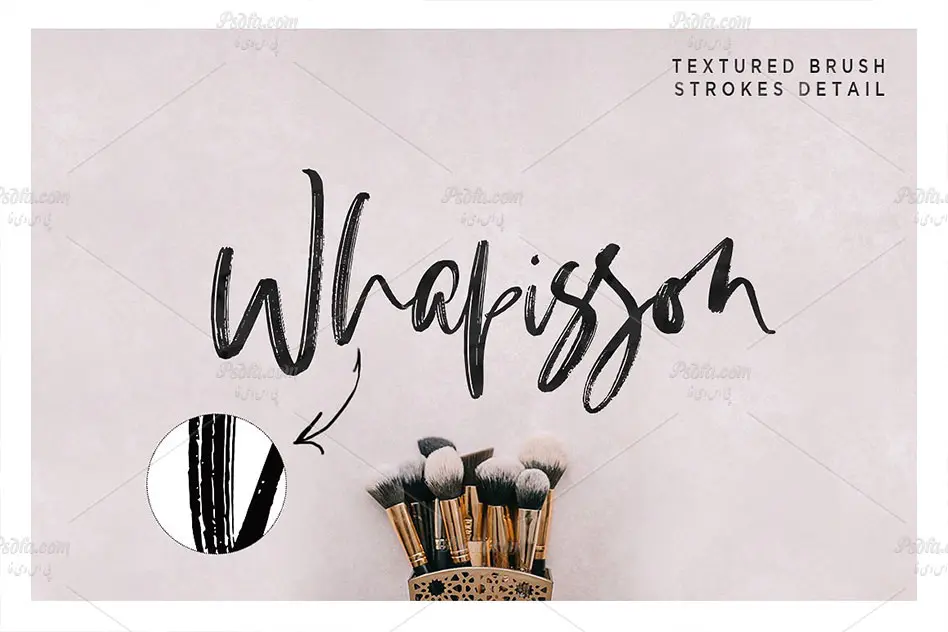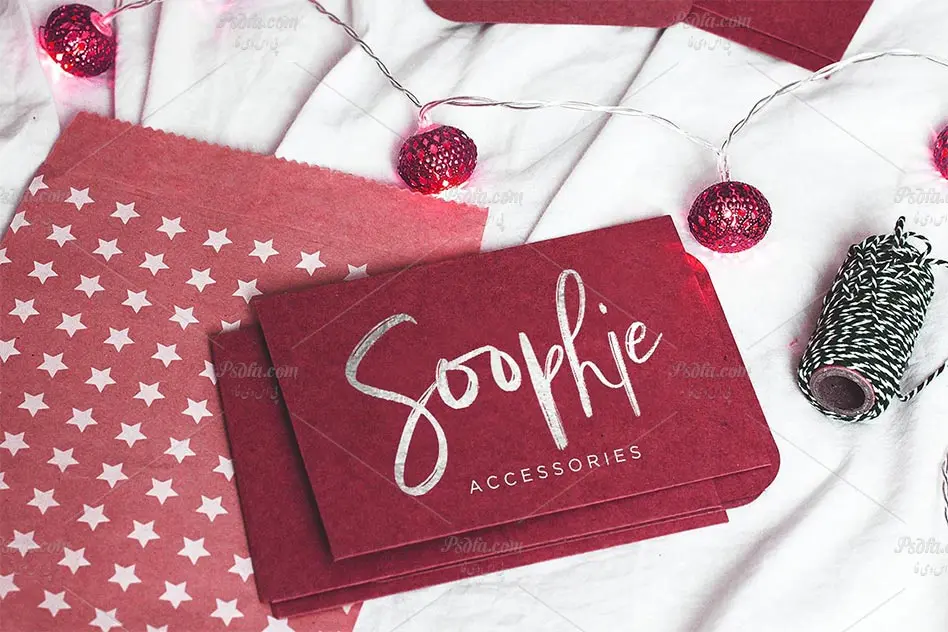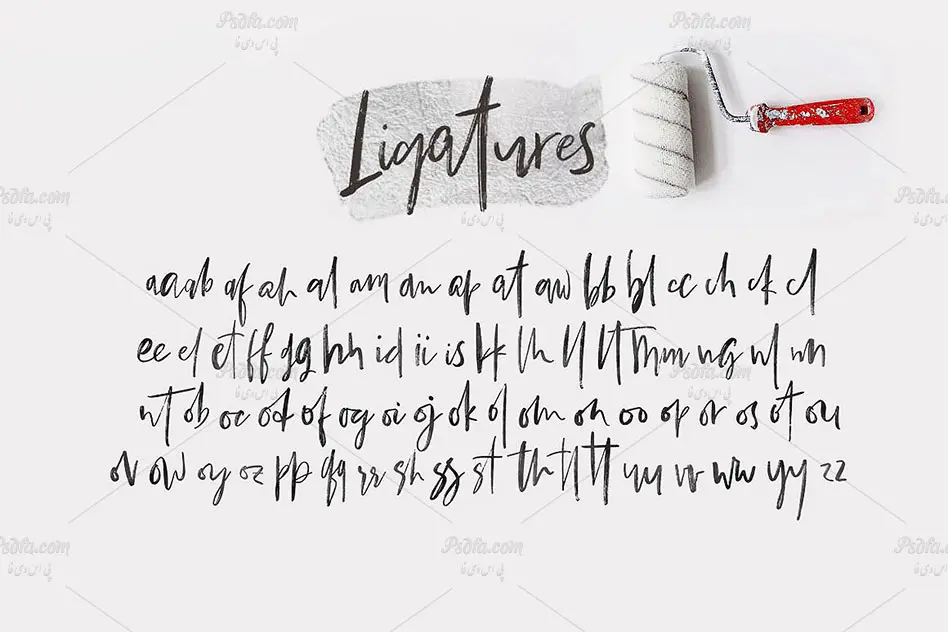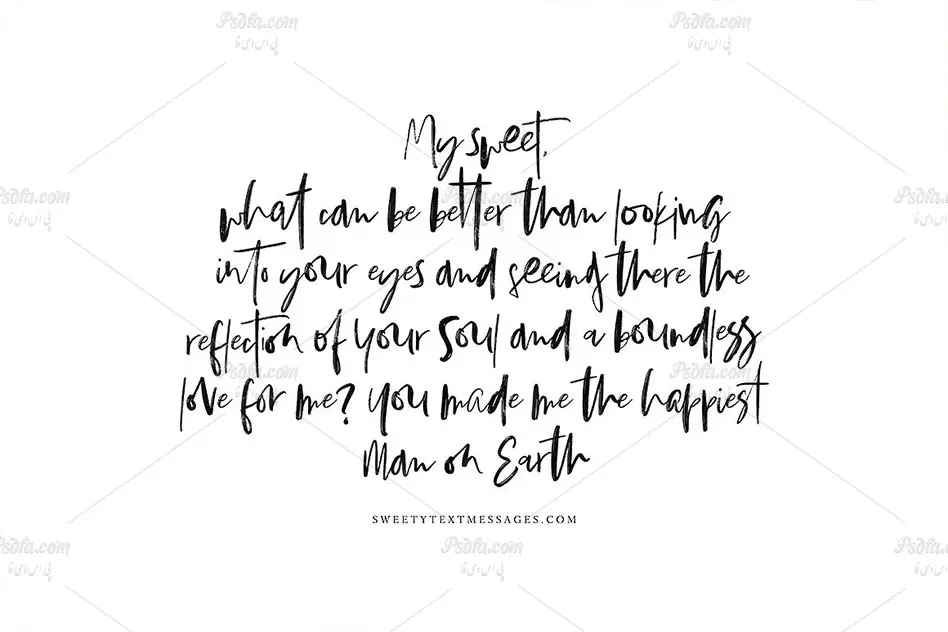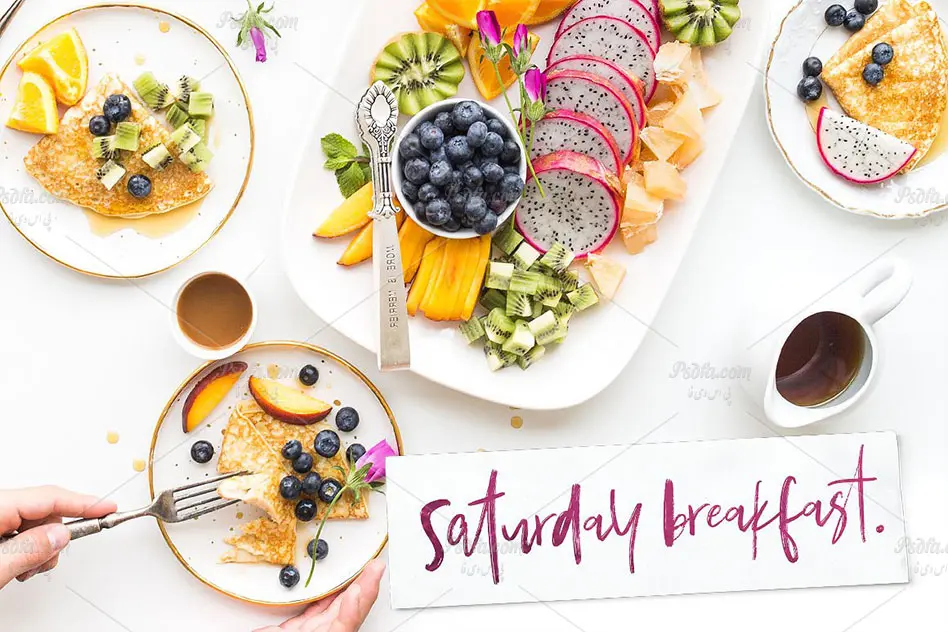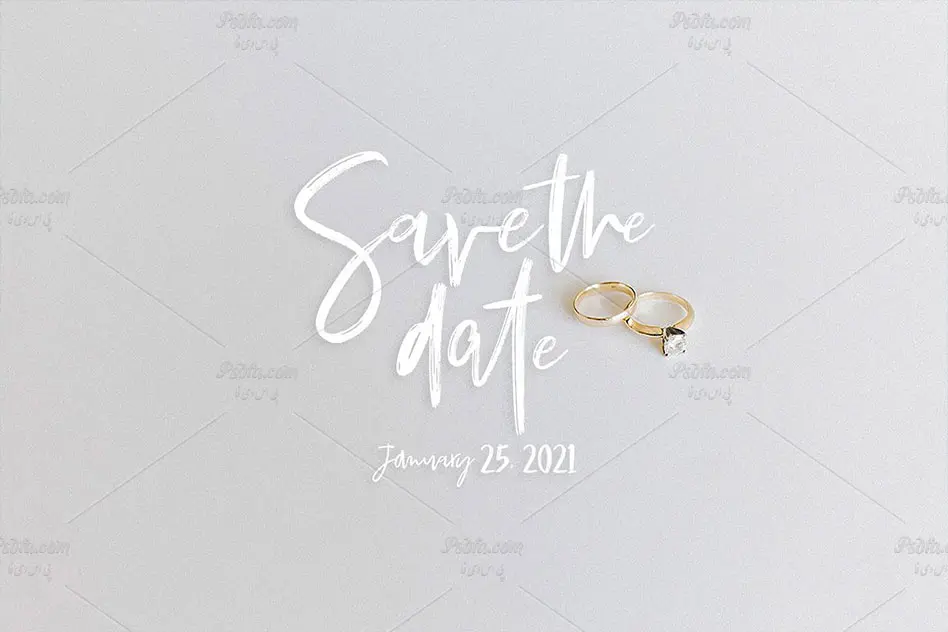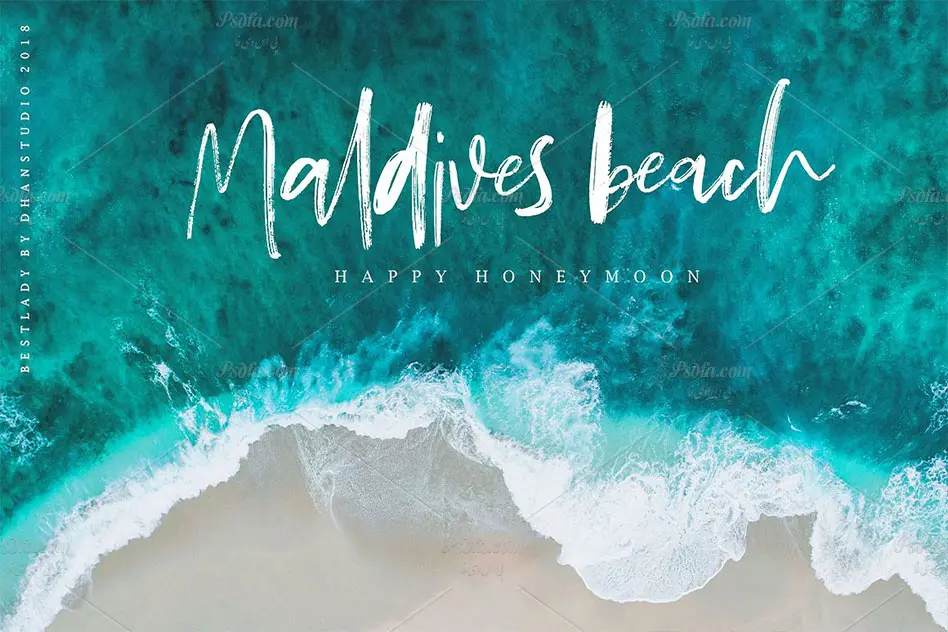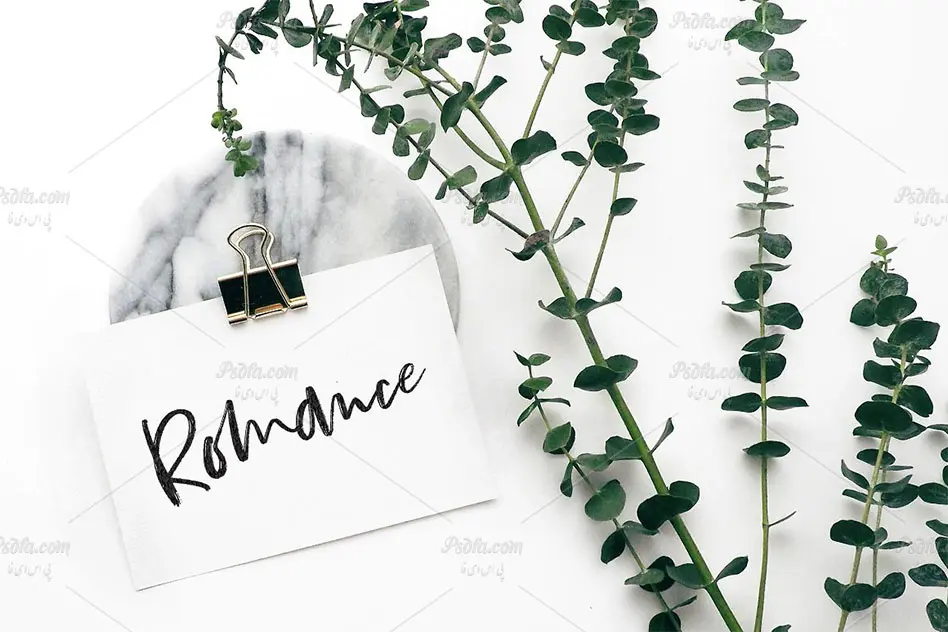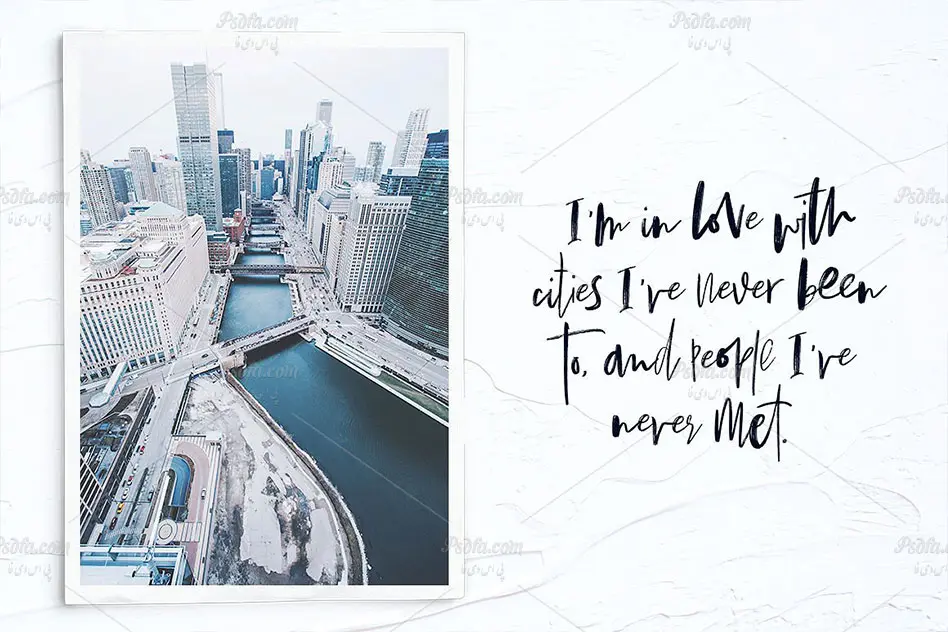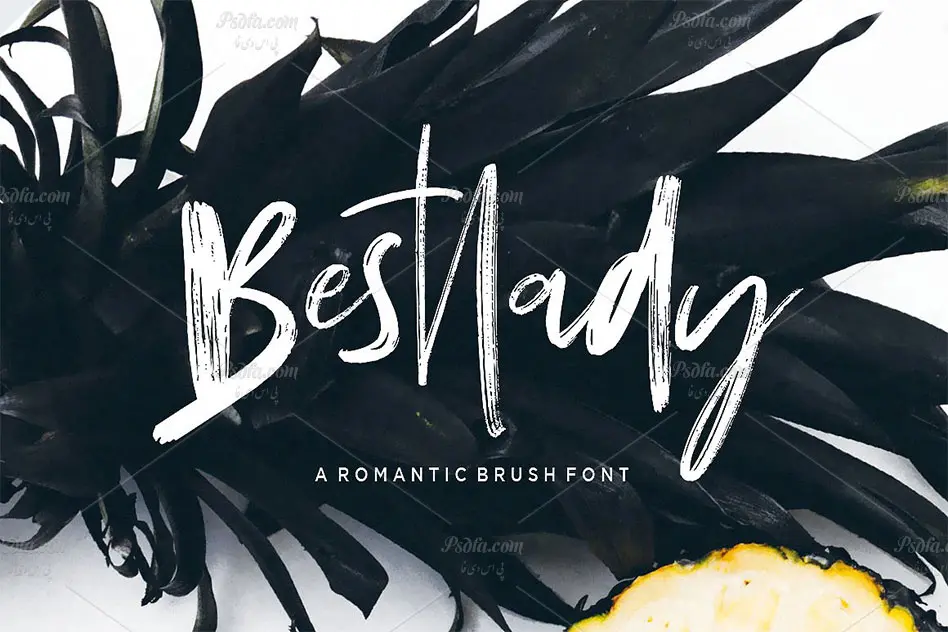
فونت قلموی انگلیسی فوق العاده زیبای Bestlady Brush Font
در این مطلب شاهد فونت قلموی انگلیسی فوق العاده زیبای Bestlady Brush Font مناسب جهت استفاده در طراحی و گرافیک می باشید. این فونت فوق العاده زیبا در قالب 2 فایل ttf و otf در سایت قرار گرفته است که با نصب هر کدام از آن ها در پوشه فونت های سیستم قادر به استفاده از آن ها در تمام نرم افزار های گرافیکی و ویرایشگر متن از جمله نرم افزار فتوشاپ ، مجموعه نرم افزار آفیس و … می باشید. این فونت که در سبک قلمویی طراحی شده است از کیفیت بالایی برخوردار بوده و مناسب جهت اجرای طرح های گرافیکی به خصوص طراحی انواع پوستر می باشد.
• طراحی در سبک قلمویی